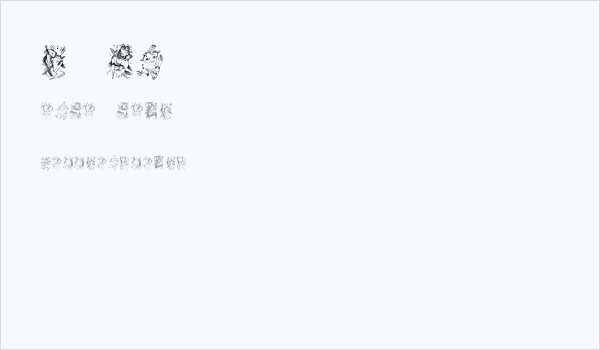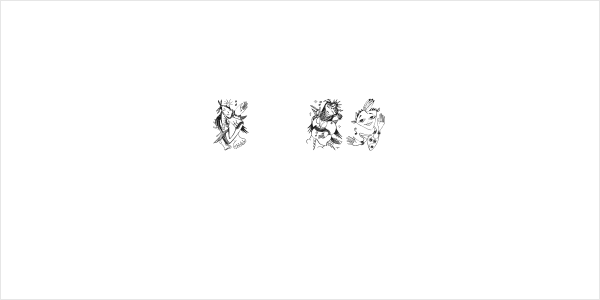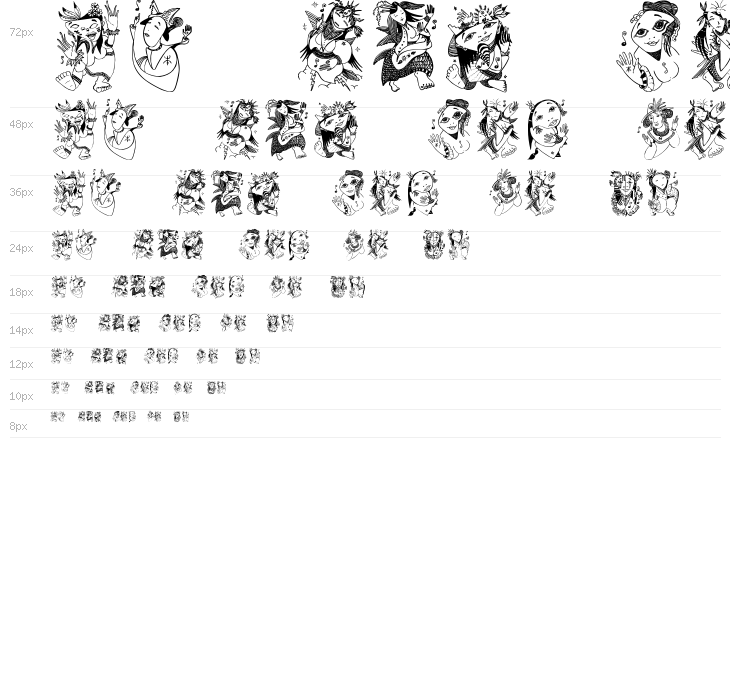
Z-Most Diva Font
| Stile generale | Artistic, Whimsical |
| Caso d'uso | Art projects, Illustrations |
| Progetti proposti | These illustrations could be used for creative projects such as graphic design artwork, posters, or unique branding elements where artistic expression is desired. |